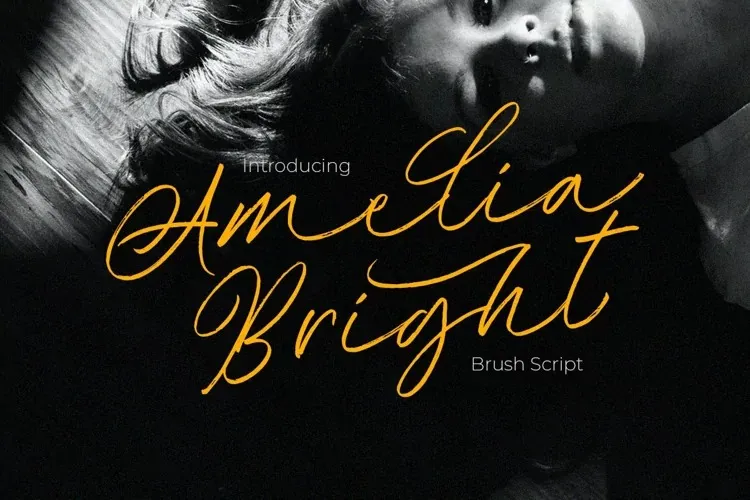
Amelia Bright é uma fonte script criada pela Letterhend Studio, inspirada nos traços de letra manual. Suas linhas fluidas e elegantes tornam a Amelia Bright perfeita para qualquer aplicação visual, desde marcas e embalagens até logotipos e convites de casamento. Esta fonte é adorável não apenas pela sua aparência sofisticada, mas também pelo fato de que foi criada através da junção de ligaturas e acabamentos finais para garantir uma textura genuína. Ela é perfeita tanto para branding, embalagens como logotipos, headlines e até mesmo convites de casamento. Com seu charme autêntico, a Amelia Bright adicionará um toque único e elegante ao design, garantindo que sua mensagem seja notada com destaque. Não importa o uso, a Amelia Bright se tornará uma escolha inegável para qualquer projeto gráfico em sua rotina diária.